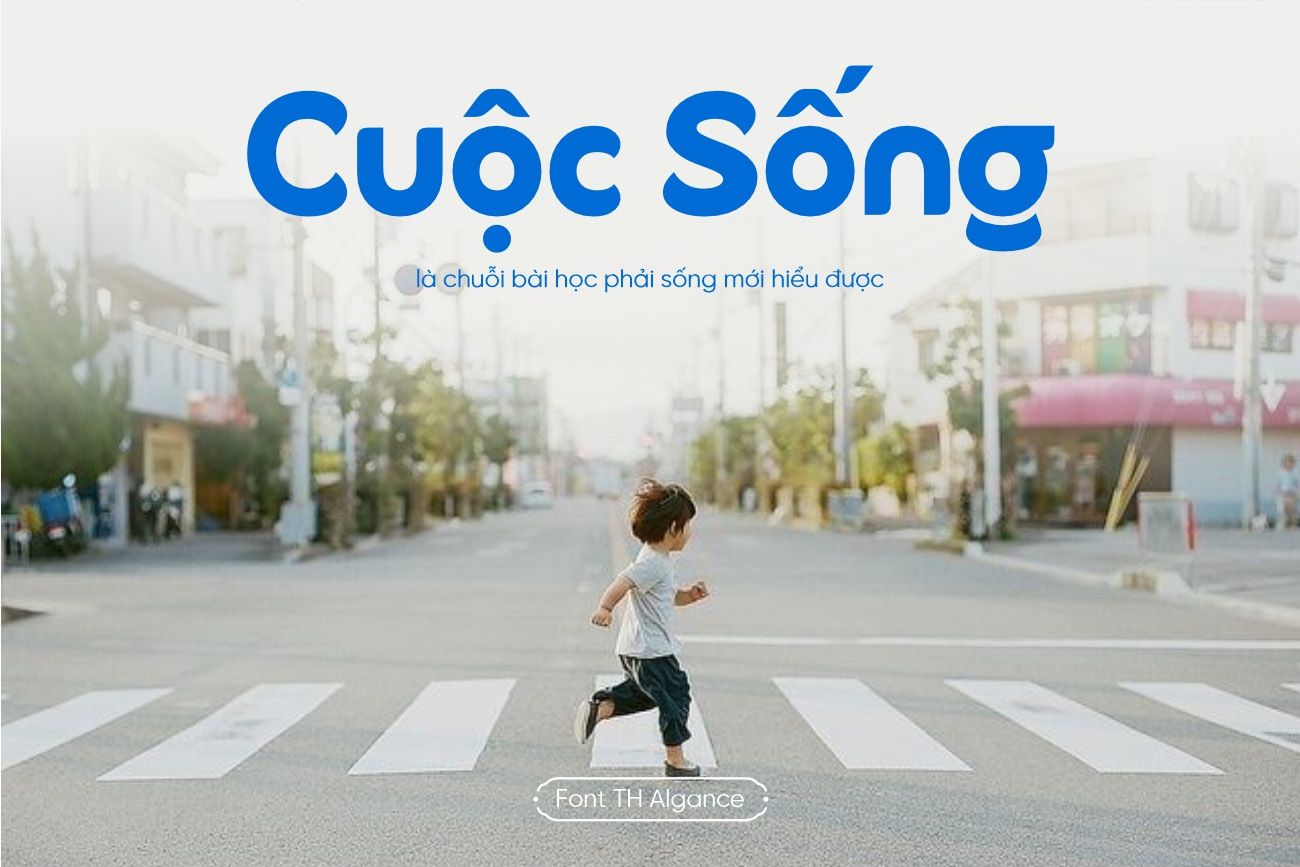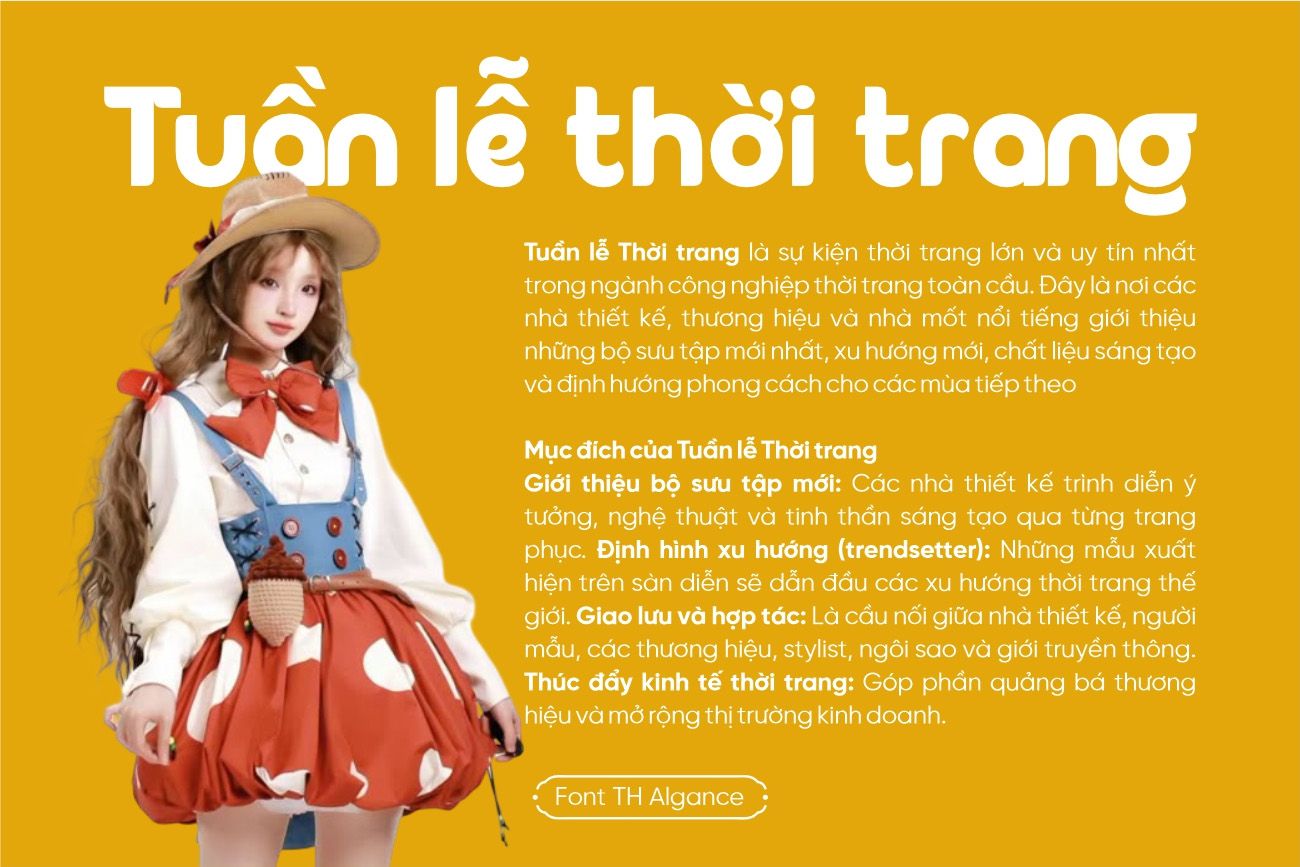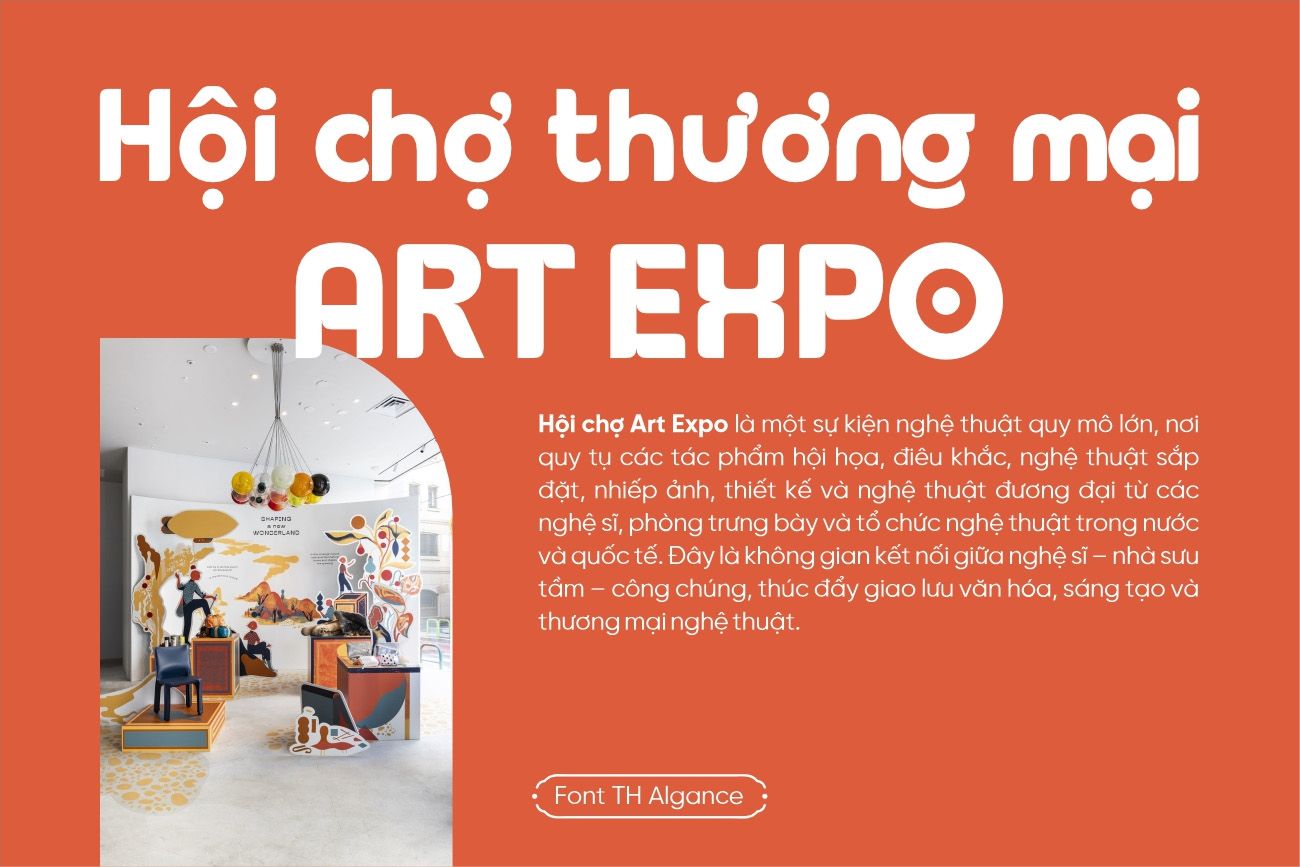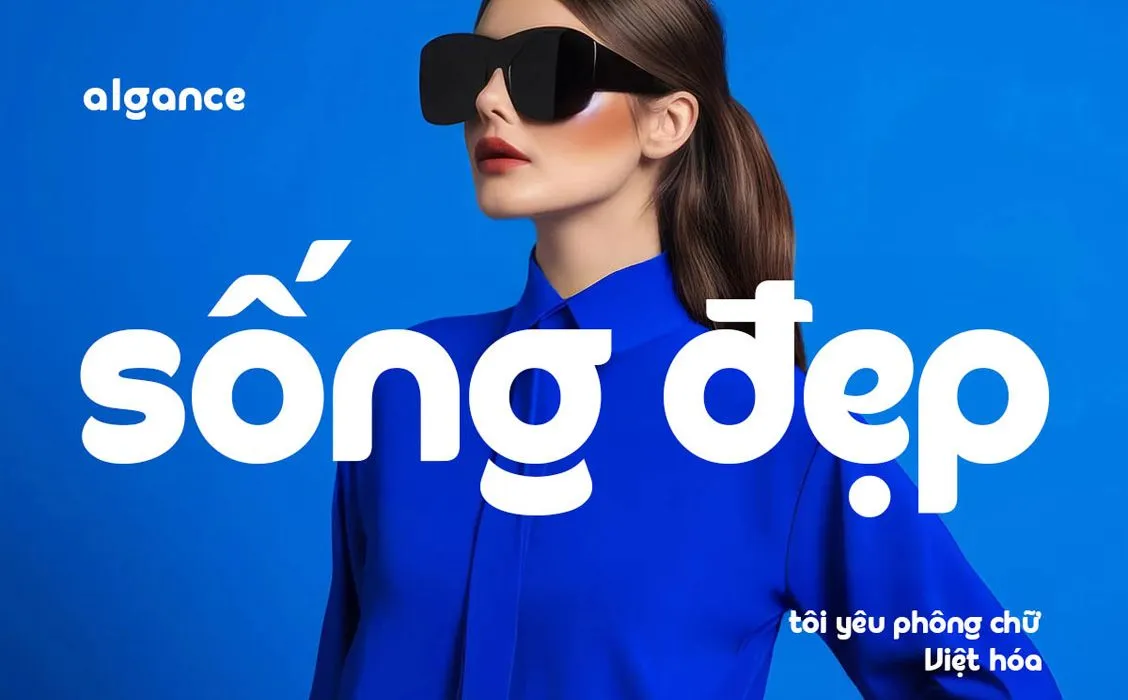
Hướng đến sự thuần khiết và tinh tế trong ngôn ngữ thiết kế, TH Algance Việt hóa là đại diện tiêu biểu cho phong cách Modern Sans Serif tối giản. Với cấu trúc các nét chữ tròn trịa, mập mạp đầy thân thiện nhưng vẫn giữ được sự chỉn chu, phông chữ này mang đến một cảm giác hiện đại, dễ gần và cực kỳ chuyên nghiệp cho mọi ấn phẩm truyền thông.
TH Algance loại bỏ những chi tiết rườm rà, tập trung vào tính ứng dụng cao và khả năng hiển thị tuyệt vời. Bản Việt hóa đã được tinh chỉnh tỉ mỉ, giúp các dấu tiếng Việt đạt được sự cân bằng hoàn hảo, không gây rối mắt ngay cả khi đứng cạnh những ký tự có độ béo (weight) lớn. Đây chính là giải pháp tối ưu cho:
Thiết kế Quotes & Trích dẫn: Tạo nên những thông điệp truyền cảm hứng đầy chiều sâu và hiện đại.
Branding cho ngành Lifestyle: Phù hợp với các thương hiệu về giáo dục, mẹ và bé, hoặc đồ gia dụng thông minh.
Layout dàn trang tạp chí: Mang lại sự thoáng đãng, dễ đọc và tinh tế cho phần tiêu đề.
Với TH Algance, thiết kế của bạn không cần quá cầu kỳ nhưng vẫn toát lên vẻ sang trọng, hiện đại và tràn đầy năng lượng tích cực.